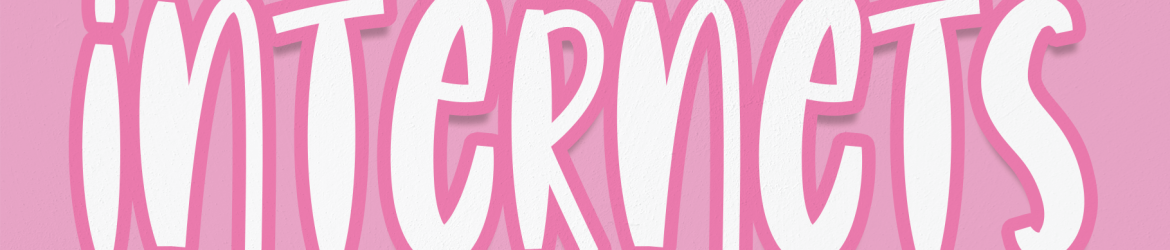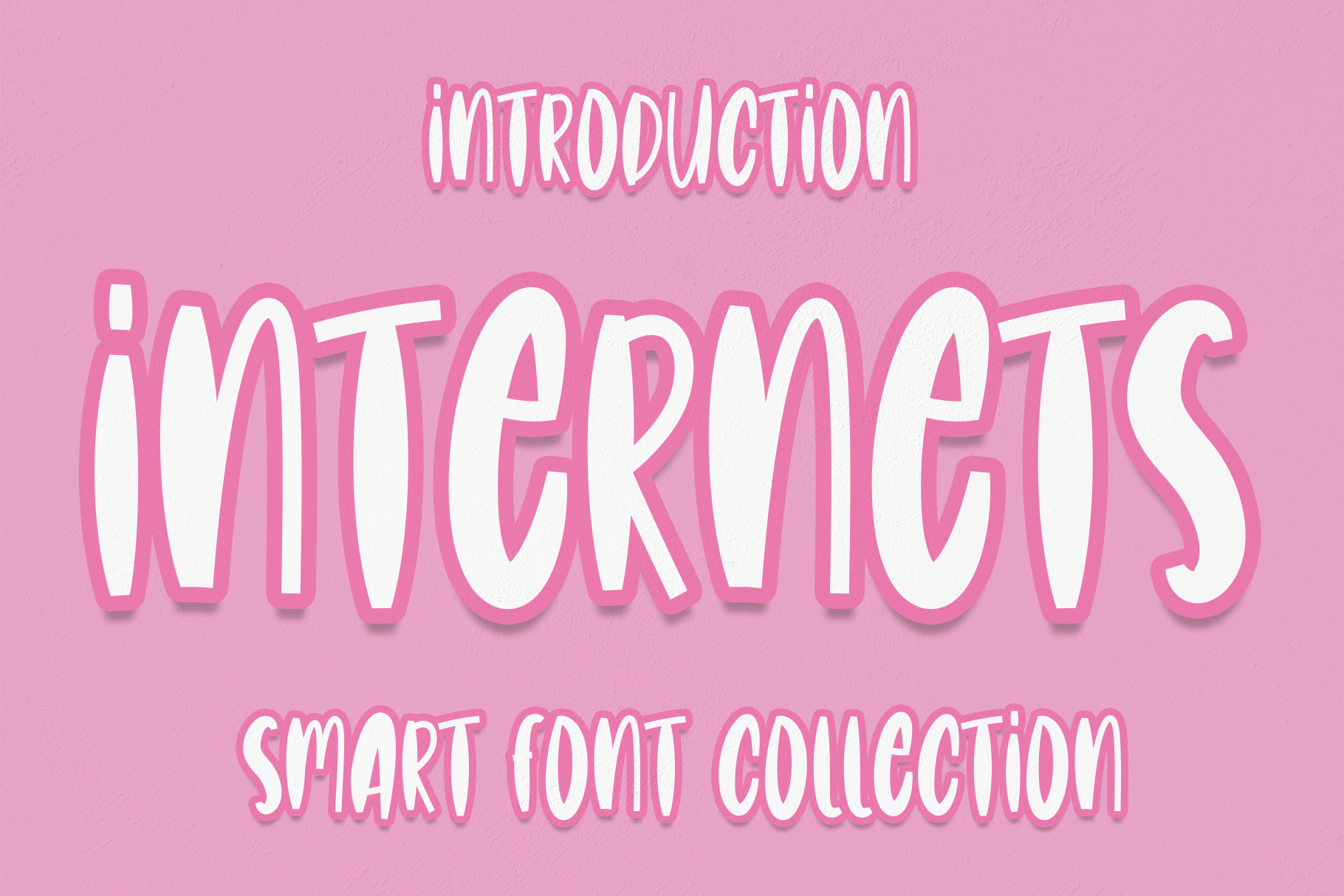
Internets Font – Fonte Grátis
Internets Font
A font Internets oferece uma experiência única para designers que buscam expressar criatividade através de letras modernas. Seu design atemporal é perfeito tanto para elementos decorativos como para aplicações digitais, especialmente no social media e em publicações de mídia social. Este design especial está à procura do seu próximo projeto visual, seja ele uma identidade visual de marca, um logotipo, uma embalagem ou até mesmo um post de rede social com a aparência autêntica da arte manual. Internets se destaca por sua capacidade de adaptar o estilo atual para múltiplas aplicações. Suas linhas levemente curveadas e formas geométricas minimalistas são perfeitas para elementos decorativos como post-its em paredes ou até mesmo adesivos para carros, mantendo seu conceito visual único e moderno. Para quem está buscando uma font que possa dar vida a qualquer projeto visual, Internets Font é um produto criativo inovador. É perfeito para designers de identidade visual, profissionais de design gráfico ou até mesmo fotógrafos em busca de criar seu próprio estilo tipográfico distintivo. Internets está disponível para aqueles que querem dar vida à sua visão e fazer dela algo único e autêntico através da fonte mais perfeita do que a existente.